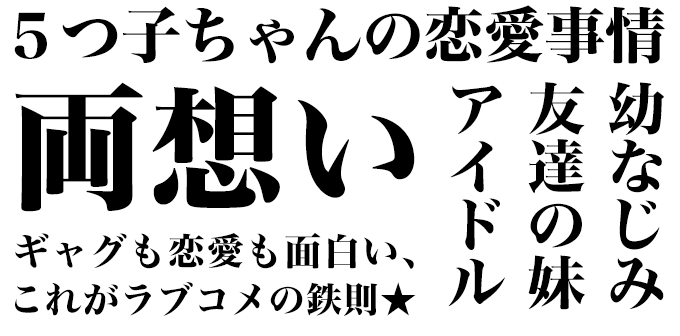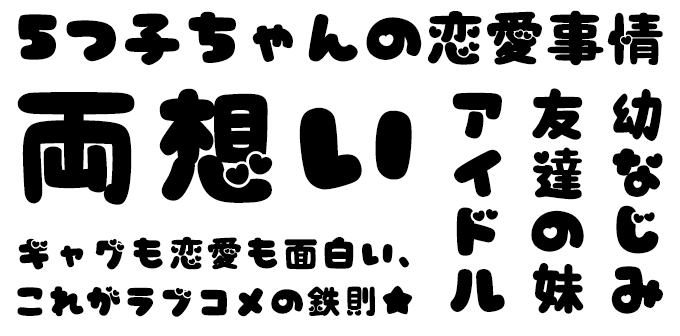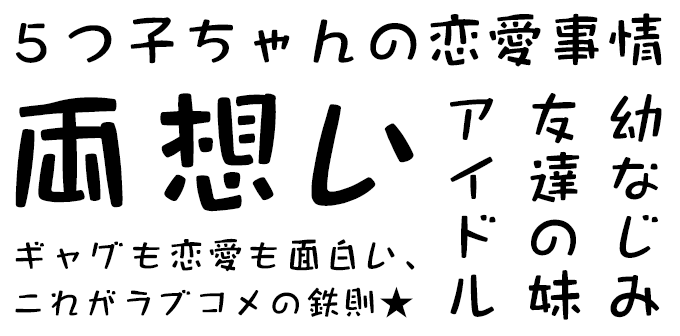
ラブコメに合うフォント 特化型 目的別フォントガイド
使用フォント:DSあかり
ラブコメに合うフォント:特化型 目的別フォントガイド #028
ラブコメに合うフォントをスタッフが選びました
ラブコメに合うフォント #1 花とちょうちょ
花とちょうちょ【鈴木メモ】
リアルに女子が書いたようなきれいな右肩上がりのフォント。メッセージを伝えたい場面で是非使ってほしいフォントです。
ラブコメに合うフォント #2 DSあかり
DSあかり【七種泰史/デザインシグナル】
角ばった律儀なフォルムと、明るく軽やかな雰囲気を両立させたフォント。TVアニメ第2期制作決定した「イジらないで、長瀞さん」のタイトルにも使用されています。
ラブコメに合うフォント #3 かりぐらスキップ
かりぐらスキップ【アトリエこたつ】
カリグラフィーペンで書いたような線の強弱のある和文書体。スキップをしているような軽快なハネが特徴的なデザインで、ラブコメにぴったりのフォントです。
ラブコメに合うフォント #4 ヒラギノ明朝 StdN W8
ヒラギノ明朝 StdN W8【ヒラギノフォント】
ビジュアル雑誌やパンフレット用に開発された明朝体ファミリー「ヒラギノ明朝」。Mac OS Xに標準搭載されていることもあり、もっともよく知られた日本語書体。「乙女ゲームの破滅フラグしかない悪役令嬢に転生してしまった…」のタイトルロゴにも使用されています。
ラブコメに合うフォント #5 DFPロマン輝 W9
DFPロマン輝 W9【ダイナフォント】
キラキラ輝いてるように見えるようなセリフが印象的なフォント。ラブコメのキラキラ感演出にいかがでしょうか。
ラブコメに合うフォント #6 TA-ゆるみん
TA-ゆるみん【FONT1000】
ゆるキャラのような明朝体というコンセプトでデザインされた愛嬌のある手書き風のフォント。ゆるい雰囲気のラブコメタイトルにぴったりのフォントです。
ラブコメに合うフォント #7 JTCじゃんけんU
JTCじゃんけんU【ニィスフォント】
ほがらか、楽しい、自然、素朴なイメージのデザイン書体。文字を組むとラブコメらしい楽しい、にぎやかなリズム感が出るフォントです。
ラブコメに合うフォント #8 JTC彩滉W8
JTC彩滉W8【ニィスフォント】
欧文ロゴデザイナーとして日本の第一人者である三浦滉平のデザイン。「はらい」のアクセントが効果的です。楽しい雰囲気が溢れるフォルムで文字を組むとラブコメらしいリズム感が出るフォントです。
ラブコメに合うフォント #9 まーと太角ゴシック
まーと太角ゴシック【CFONT】
角ばった字形の太角ゴシック体のフォントです。遊び心の中に多少の真面目さを表現する際に使えそうなフォントです。「この素晴らしい世界に祝福を」のコミック版のタイトルでも使用されています。
ラブコメに合うフォント #10 ましゅまろポップ ハート
ましゅまろポップ ハート【かに沢のりお】
<p style=マシュマロのようにぽってり太め、ぷにぷにと丸っこいフォントです。ハートがあちこちにまぎれていてラブコメのタイトルらしいデザインのフォントです。
ラブコメに合うフォント #11 はちまるポップ
はちまるポップ【かに沢のりお】
1970から80年代に流行した、丸文字をイメージしたファンシーで丸っこいフォントです。かわいらしい雰囲気がラブコメタイトルに最適なデザインのフォントです。
ラブコメに合うフォント #12 ARなごみPOP体B
ARなごみPOP体B【アーフィック】
太くハッキリとしていながら、やさしい印象の書体です。かわいらしい雰囲気がラブコメタイトルにぴったりのフォントです。
ラブコメに合うフォント #13 TA-丸花巻
TA-丸花巻【FONT1000】
絶妙なアンバランス感と強い個性を持ちながらも、可読性も考慮され、文字組すると軽やかなリズムが生まれるデザインでラブコメタイトルにぴったりのフォントです。